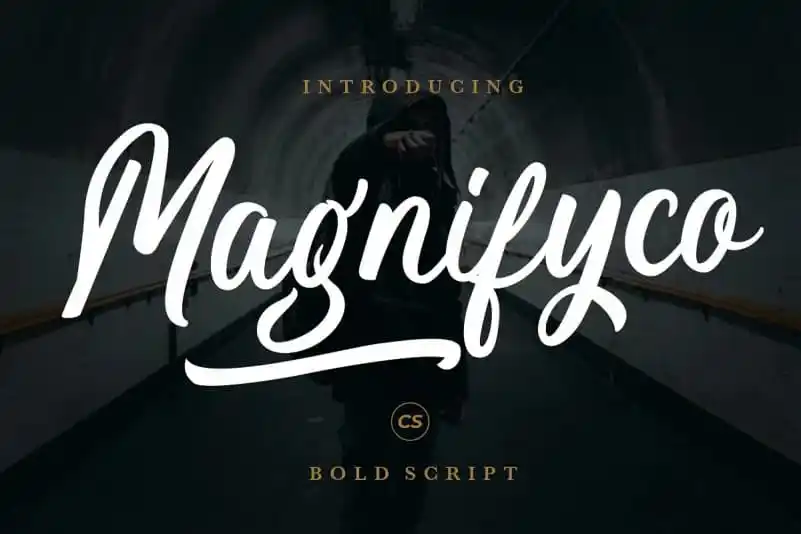
A Magnifyco Brush Font é uma opção perfeita para aqueles que buscam um estilo elegante e autêntico, com linhas firmes e formas limpas. Pertencente à categoria de Fonts de Truques Escritos, ela oferece o charme pessoal necessário para projetos diversas. Seja para criar uma identidade forte em sua marca, desenhar logomarcas memoráveis, adicionar um toque delicado a postagens nas redes sociais, estampar suas anúncios com sofisticação, personalizar embalagens de produtos ou mesmo decorar etiquetas e cartões de visita, esta fonte tem tudo para tornar seu trabalho impecável. Com Magnifyco Brush Font, você pode garantir que qualquer projeto seja envolventemente atraente, destacando-se de forma única em qualquer meio. Seja você um fotógrafo buscando dar vida à sua arte ou uma designer gráfica criando identidades visuais memoráveis, essa fonte é um aliado imprescindível para quem busca estilo e personalidade nas suas criações.